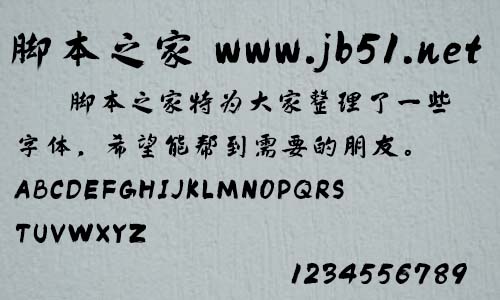
方正俠客體字體筆觸較為粗實(shí),字體書(shū)寫(xiě)端正大氣,具有很好的視覺(jué)感,適合應(yīng)用于藝術(shù)設(shè)計(jì)、平面宣傳設(shè)計(jì)、網(wǎng)頁(yè)設(shè)計(jì),書(shū)法字帖等領(lǐng)域。
方正俠客體的創(chuàng)作源自設(shè)計(jì)《評(píng)書(shū)聶隱娘》出版物,寫(xiě)字如揮劍,講究輕重緩急,當(dāng)時(shí)希望用這種斬釘截鐵的率性書(shū)寫(xiě)來(lái)呈現(xiàn)俠客的瀟灑與果敢。 古人云:“隨心所欲不逾矩”,我們必須尊重傳統(tǒng)、敬畏傳統(tǒng),在此基礎(chǔ)上創(chuàng)作出具有時(shí)代特色的作品,俠客體的創(chuàng)作就是基于這樣的理念。師法古代經(jīng)典碑帖,比如顏真卿、張即之、朱熹等名家作品,字形以行楷為基準(zhǔn),盡可能保留筆畫(huà)的豐富性,比如粗細(xì)變化、相同偏旁部首的變化以及飛白的效果等。作者希望創(chuàng)作一種既符合傳統(tǒng)書(shū)法的筆法與結(jié)構(gòu),又能具有視覺(jué)設(shè)計(jì)張力的書(shū)法標(biāo)題字體。主要適用于廣告、包裝、影視劇的標(biāo)題等。